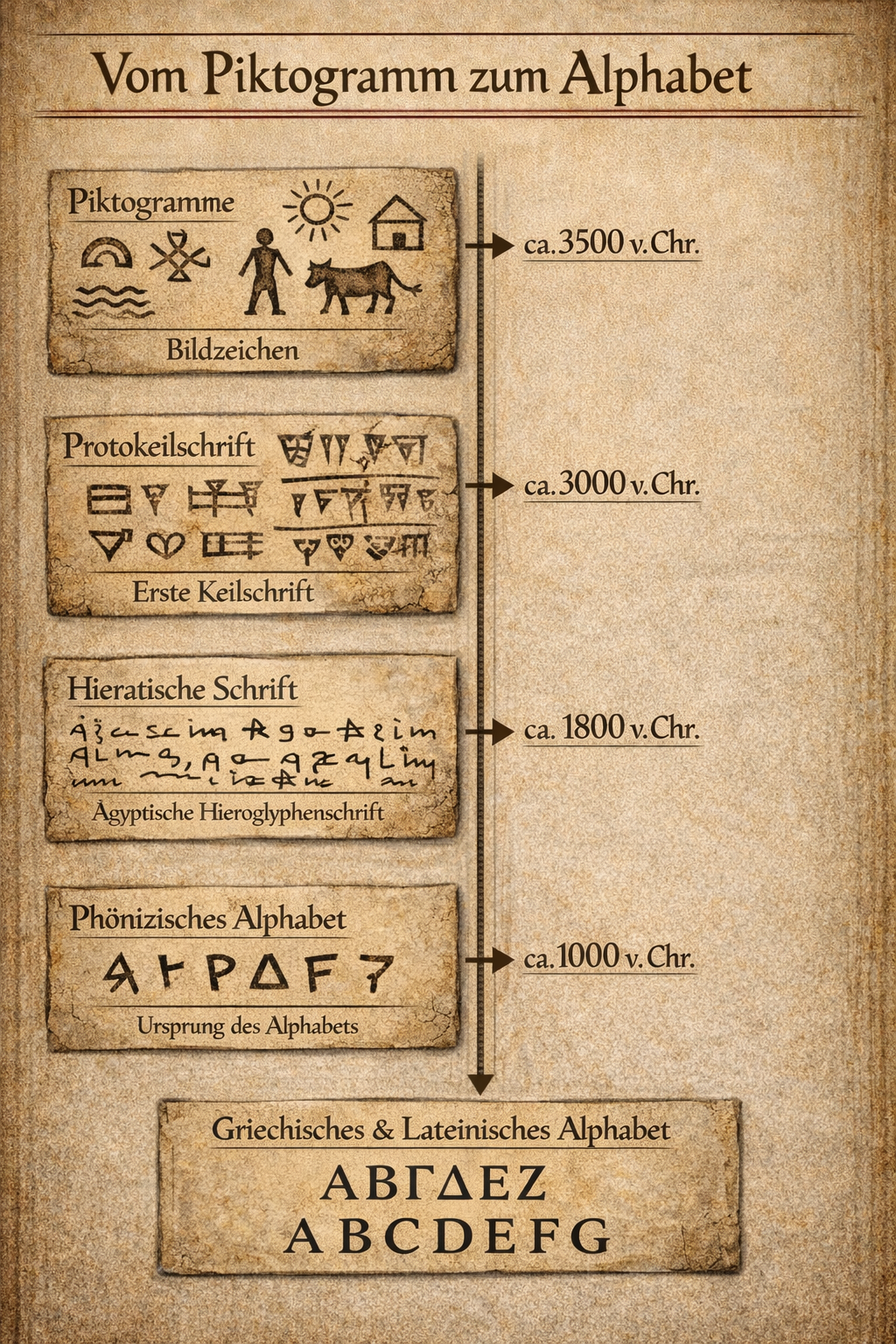
Viele unserer Buchstaben tragen noch immer das ursprüngliche Bildmotiv in sich: Das hebräische „Aleph“ war einmal ein Ochsenkopf, das „Beth“ ein Haus, das „Mem“ stand für Wasser. Über die Phönizier, Griechen und Römer wanderten diese Zeichen durch das Mittelmeer — und verwandelten sich Schritt für Schritt in die Buchstaben A, B und M, die wir heute kennen.
Piktogramm-Alphabet
Am Anfang stand das Bild: Ein Ochsenkopf, ein Haus, ein Wasserstrahl. Mit der Zeit wurden aus Bildzeichen Lautzeichen — und aus dem Piktogramm entstand das Alphabet, mit dem wir bis heute schreiben.
Vom Bild zum Buchstaben
Das Piktogramm-Alphabet